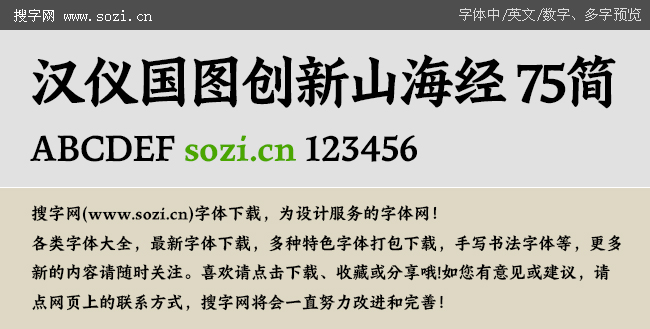
漢儀國(guó)圖創(chuàng)新山海經(jīng) 75簡(jiǎn)
搜字網(wǎng)給大家提供一款漢儀國(guó)圖創(chuàng)新山海經(jīng) 75簡(jiǎn)中文字體下載,漢儀國(guó)圖創(chuàng)新山海經(jīng)字體是一款充滿古典韻味的字體,其設(shè)計(jì)靈感來(lái)源于中國(guó)古代的山海經(jīng)。這款字體的特點(diǎn)是筆畫線條流暢,字形簡(jiǎn)潔大方,有一種古樸而莊重的感覺。適用于畫冊(cè)設(shè)計(jì)、海報(bào)設(shè)計(jì)、包裝設(shè)計(jì)等場(chǎng)合使用。(本字體為個(gè)人非商用版,如需要商用請(qǐng)聯(lián)系漢儀公司購(gòu)買版權(quán))